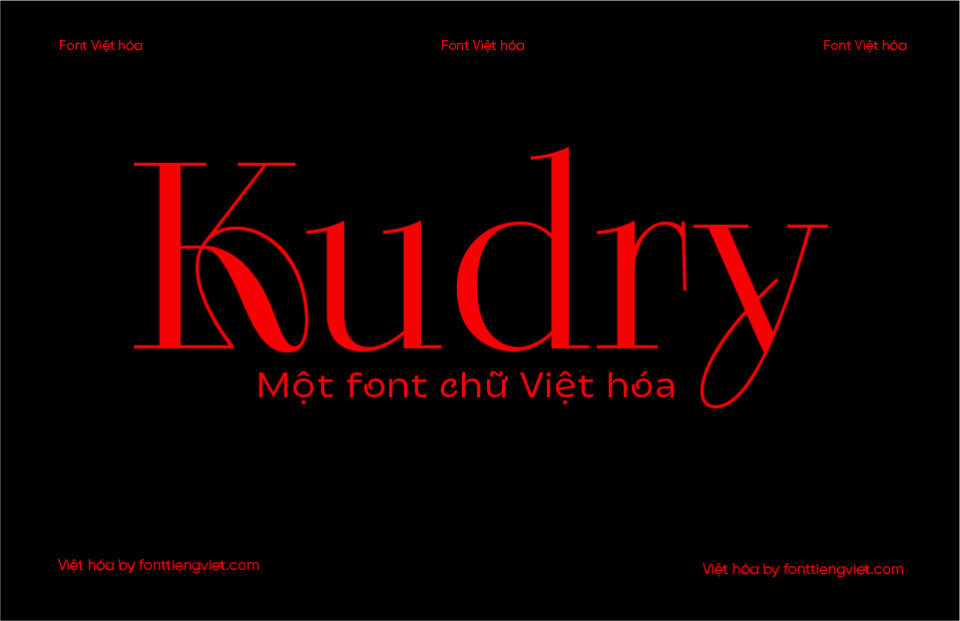
Font Việt hóa 1FTV VIP Kudry
Trong thế giới đồ họa hiện đại, việc lựa chọn một bộ phông chữ vừa mang tính nghệ thuật vừa đảm bảo tính ứng dụng cao là điều vô cùng quan trọng. Font Việt hóa 1FTV VIP Kudry nổi lên như một sự lựa chọn hàng đầu cho các nhà thiết kế tại Việt Nam nhờ vào đường nét tinh tế và phong cách sang trọng. Đây là một bộ Font Miễn Phí lý tưởng để tạo nên những ấn phẩm truyền thông chuyên nghiệp từ bìa sách, poster cho đến các tài liệu học tập sinh động. Với sự tỉ mỉ trong quá trình Việt hóa, bộ font này giúp người dùng dễ dàng gõ tiếng Việt có dấu mà không lo bị lỗi hiển thị, mang lại sự đồng nhất tuyệt đối cho mọi văn bản.
Đặc điểm nổi bật của bộ Font Việt hóa 1FTV VIP Kudry
Phong cách thiết kế hiện đại và thanh lịch
Bộ Font Việt hóa 1FTV VIP Kudry được lấy cảm hứng từ những đường nét cổ điển pha chút hơi hướng tương lai. Các ký tự có độ tương phản cao, tạo cảm giác mạnh mẽ nhưng vẫn giữ được sự mềm mại cần thiết. Điều này giúp bộ font trở nên cực kỳ linh hoạt, phù hợp cho cả tiêu đề lớn lẫn các đoạn văn bản ngắn. Trong môi trường học đường, giáo viên và học sinh có thể sử dụng font này để thiết kế các bài thuyết trình PowerPoint, làm cho nội dung bài giảng trở nên lôi cuốn và dễ tiếp thu hơn đối với người xem.
Tối ưu hóa khả năng hiển thị tiếng Việt
Một trong những ưu điểm lớn nhất của Font Việt hóa 1FTV VIP Kudry chính là sự chăm chút trong các dấu thanh. Tác giả bản Việt hóa đã điều chỉnh vị trí các dấu sắc, huyền, hỏi, ngã, nặng sao cho cân đối và hài hòa nhất với các chữ cái gốc. Điều này giúp văn bản giữ được vẻ thẩm mỹ nguyên bản mà không bị rối mắt. Khi sử dụng bộ font này, bạn sẽ nhận thấy sự khác biệt rõ rệt so với các phông chữ hệ thống thông thường, từ đó nâng tầm giá trị cho mọi dự án sáng tạo cá nhân.
Ứng dụng thực tế của Font Việt hóa 1FTV VIP Kudry trong đời sống
Sử dụng trong thiết kế đồ họa và in ấn
Nhờ vào cấu trúc ký tự đặc biệt, Font Việt hóa 1FTV VIP Kudry thường xuyên được các designer ưu ái lựa chọn cho các dự án nhận diện thương hiệu hoặc thiết kế bao bì cao cấp. Khả năng gây ấn tượng thị giác mạnh mẽ giúp sản phẩm nổi bật giữa đám đông. Ngoài ra, với định dạng hỗ trợ tốt cho in ấn, các chi tiết nhỏ của font vẫn hiển thị sắc nét trên các chất liệu giấy khác nhau, từ giấy mỹ thuật đến bạt hiflex thông thường.
Hỗ trợ học tập và giảng dạy hiệu quả
Đối với các em học sinh, việc tiếp cận với những bộ font đẹp như Font Việt hóa 1FTV VIP Kudry giúp kích thích tư duy thẩm mỹ và sự hứng thú trong việc trang trí báo tường hoặc làm tập san lớp. Các thầy cô giáo cũng có thể dùng font này để làm tiêu đề cho các đề kiểm tra hoặc bằng khen khen thưởng, tạo nên sự trang trọng và khích lệ tinh thần học tập. Đây thực sự là một công cụ hữu ích cho bất kỳ ai muốn truyền tải thông điệp một cách ấn tượng và đầy cảm hứng.
Tóm lại, việc sở hữu bộ Font Việt hóa 1FTV VIP Kudry sẽ mang đến cho bạn một luồng gió mới trong tư duy thiết kế. Sự kết hợp hoàn hảo giữa tính thẩm mỹ và công năng sử dụng giúp bộ font này trở thành người bạn đồng hành tin cậy cho mọi dự án. Hãy khám phá ngay thế giới Font Miễn Phí, Font Việt Hóa, Font Việt hóa 1FTV VIP Kudry để biến những ý tưởng trên trang giấy thành hiện thực sinh động và chuyên nghiệp nhất ngay hôm nay.